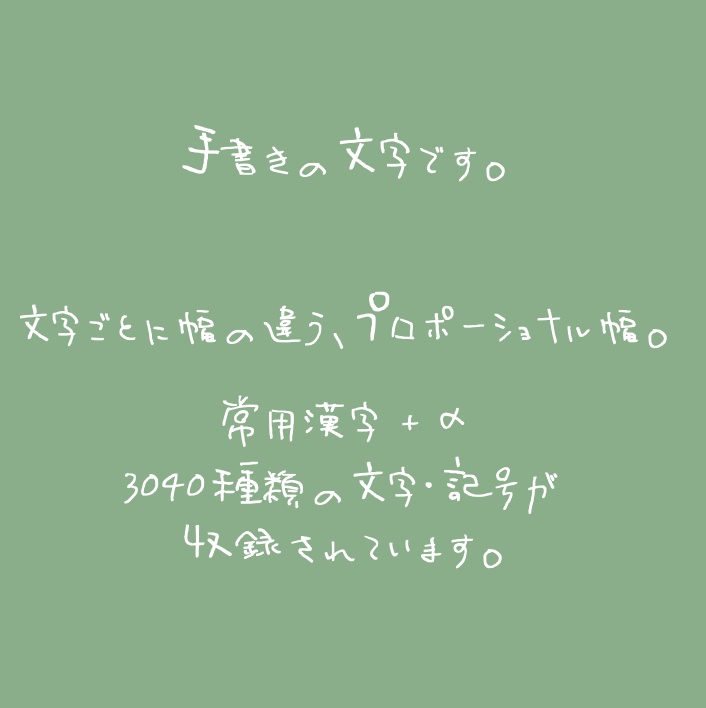
手書き癖字日本語フォント「ちゃんずフォント」
手書きの日本語フォントです。癖字です。
✏️概要
常用漢字+α、計3040種類の文字・記号が収録されています。 現時点でアップデート予定はありませんが、気が向いたら収録文字数を増やすかもしれません。 https://buttaiwan.github.io/writemyfont/ja.html こちらのツールを使って作成しました。